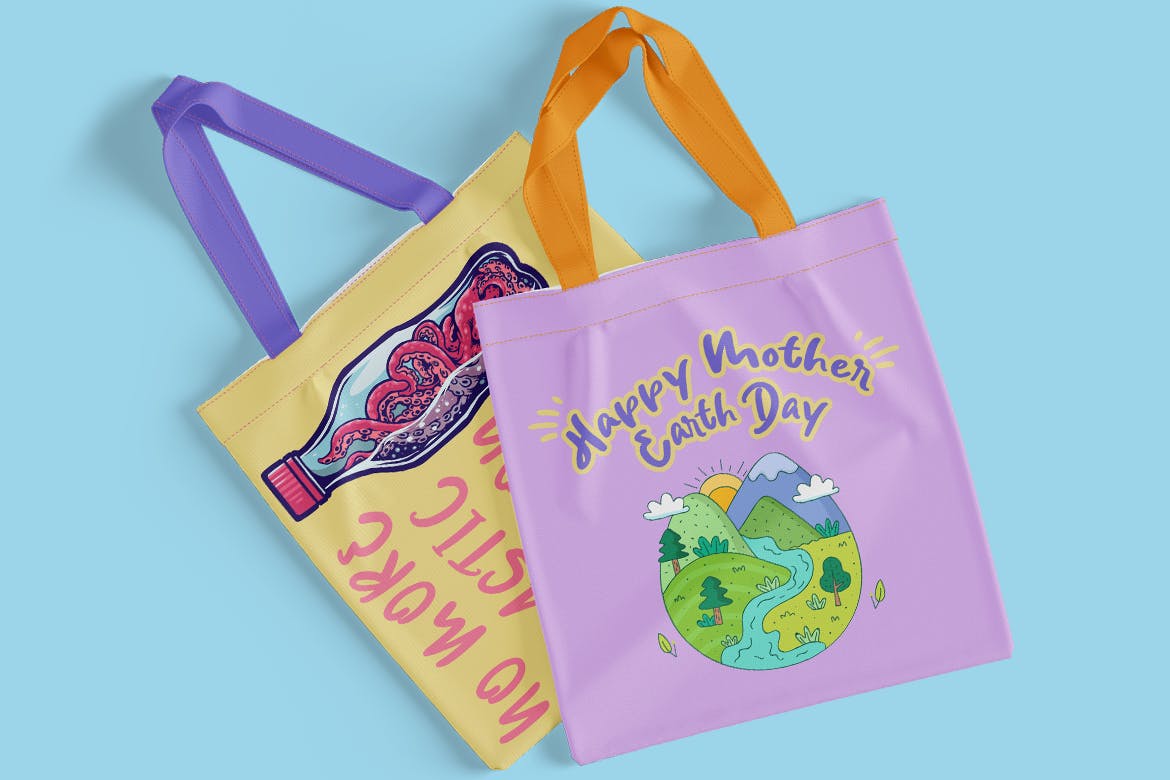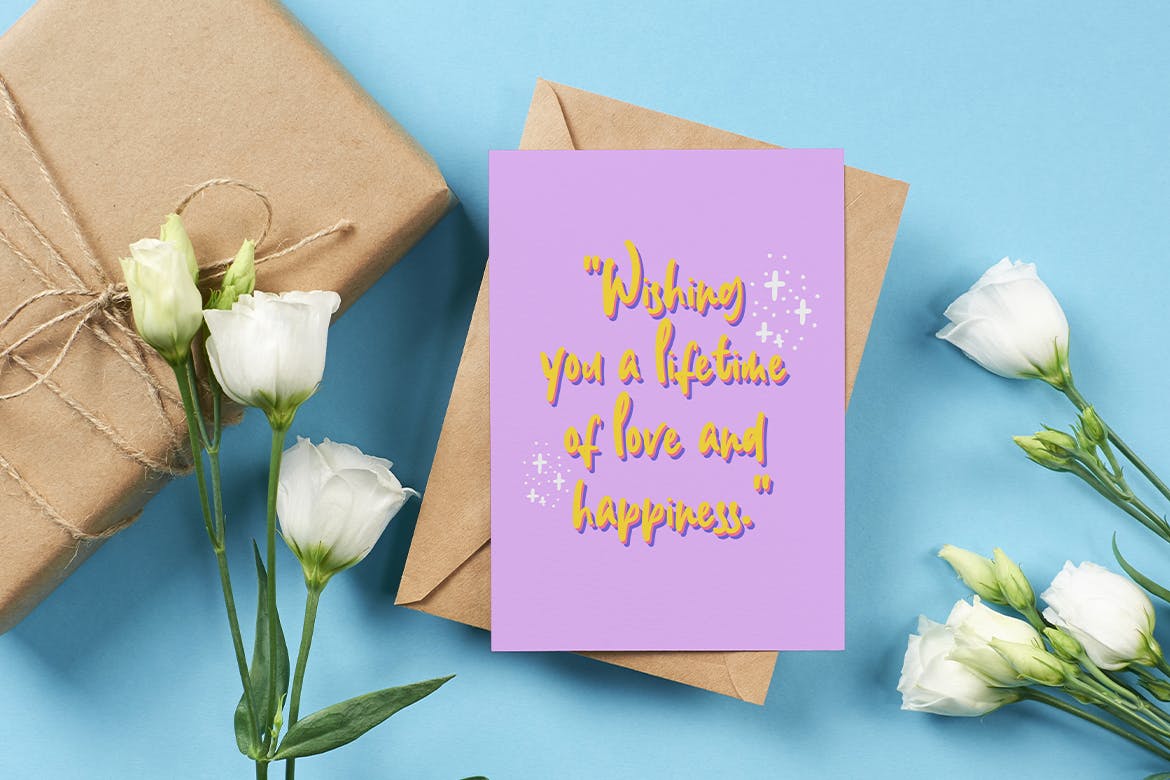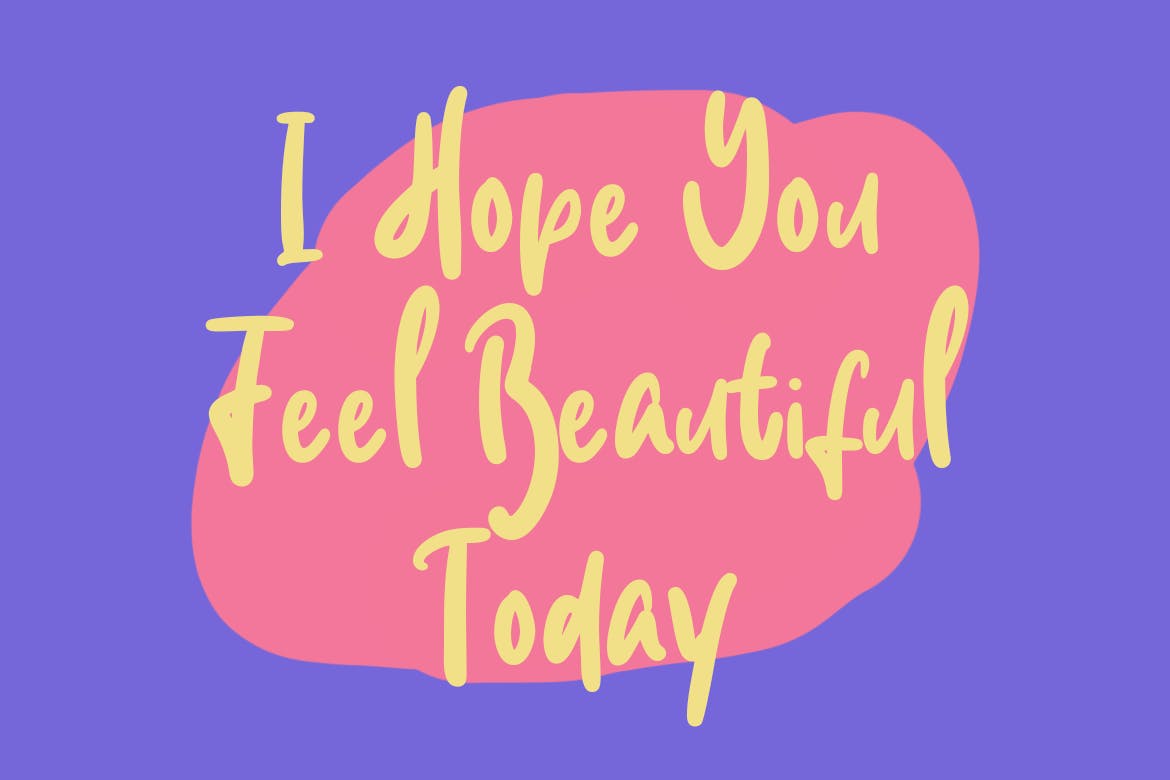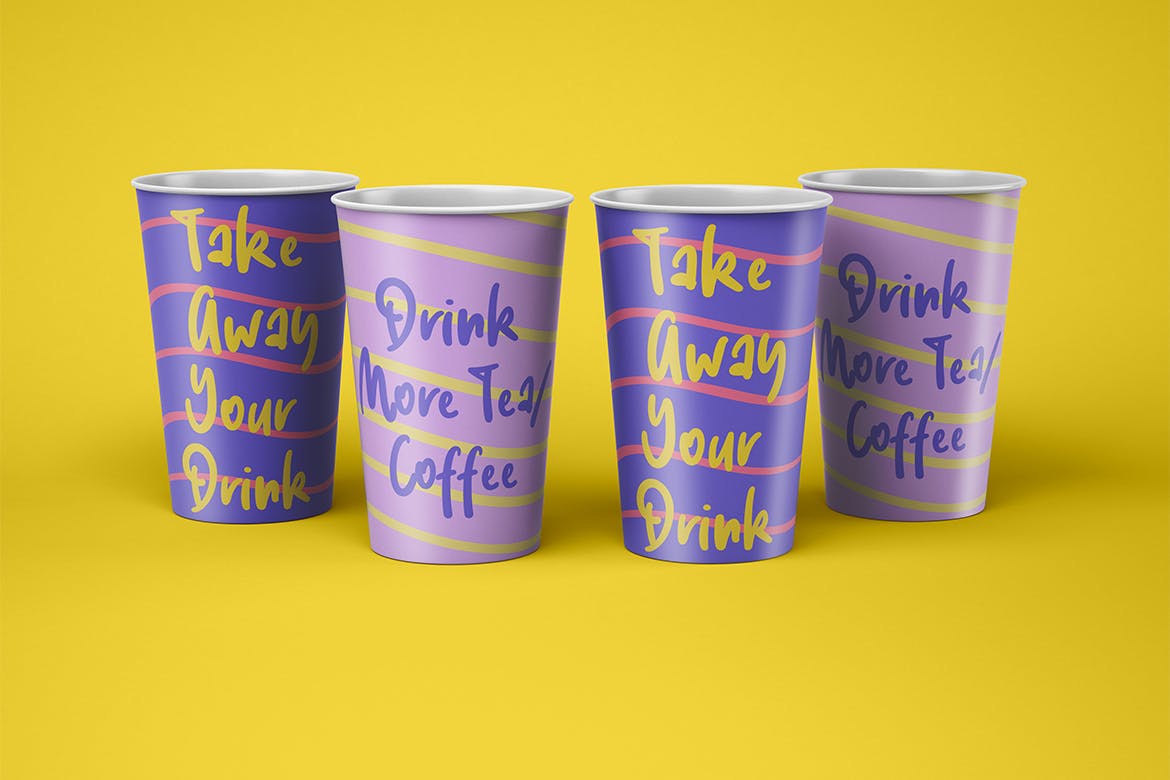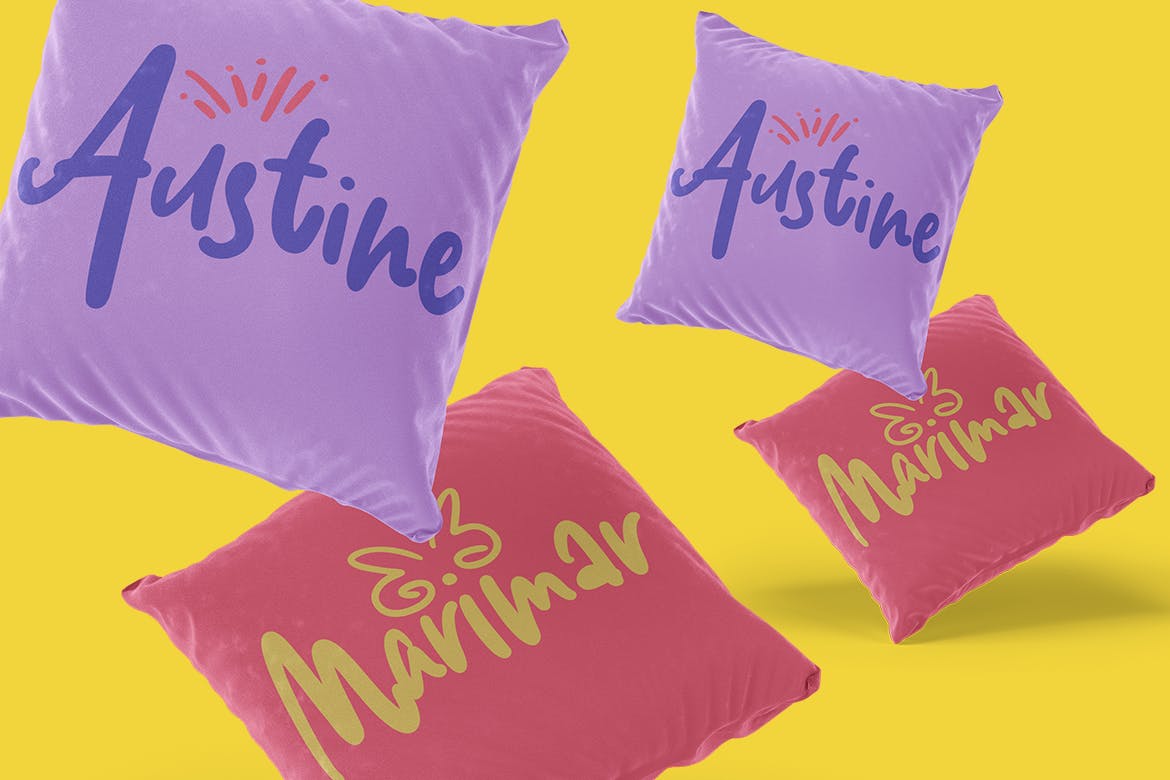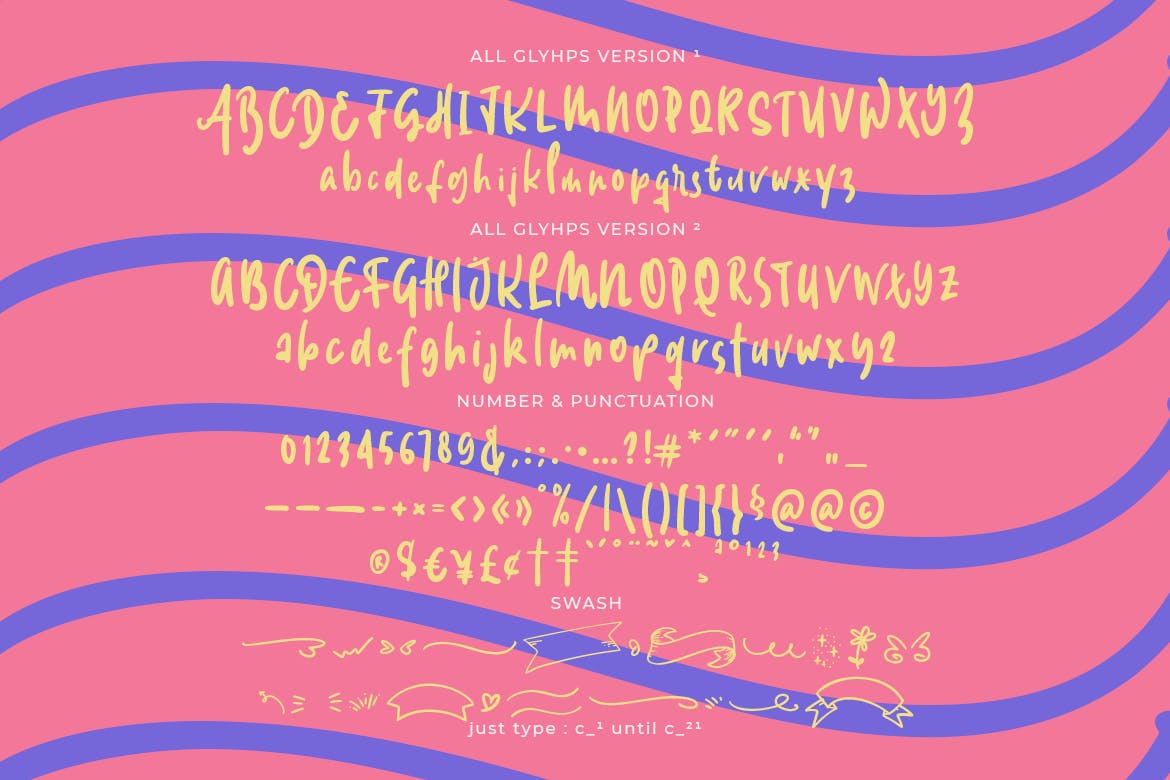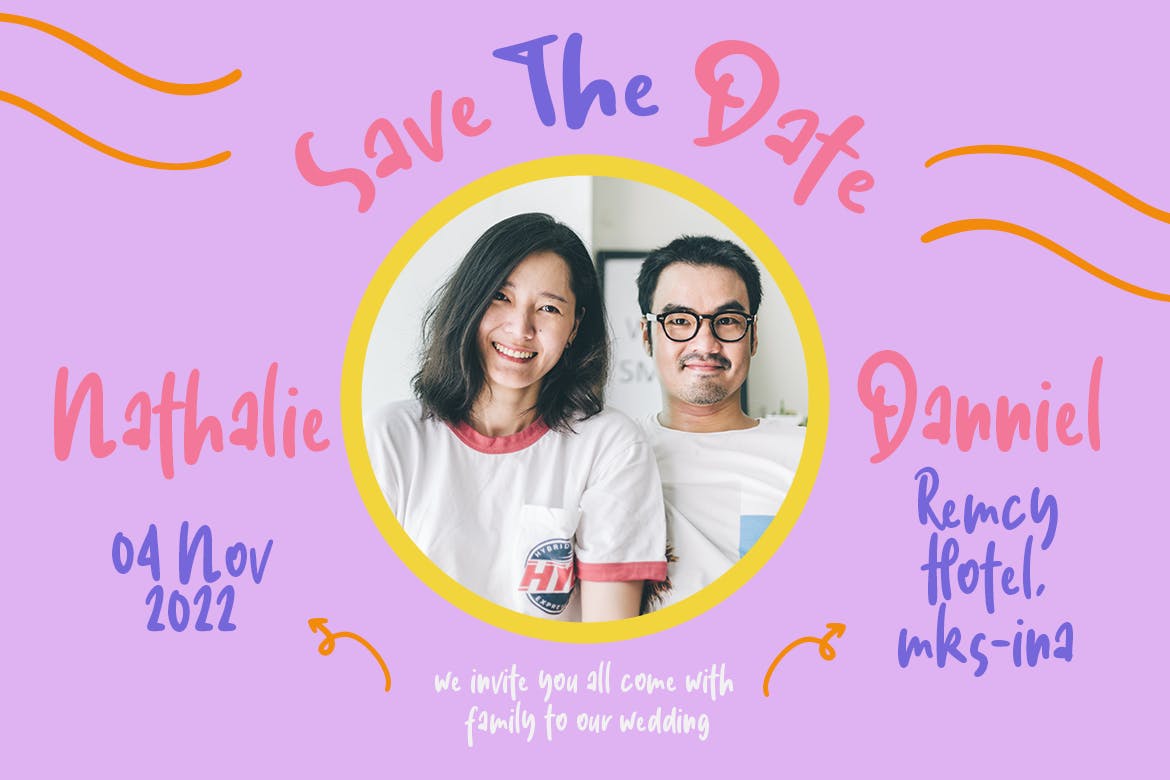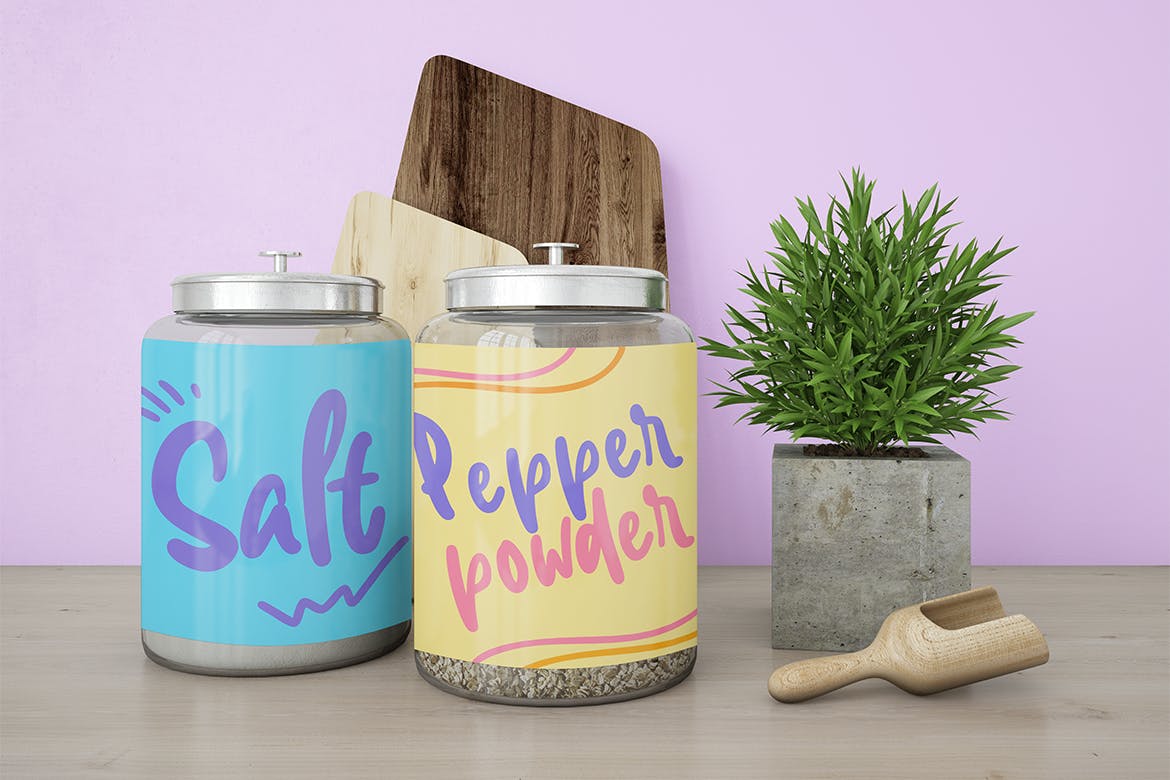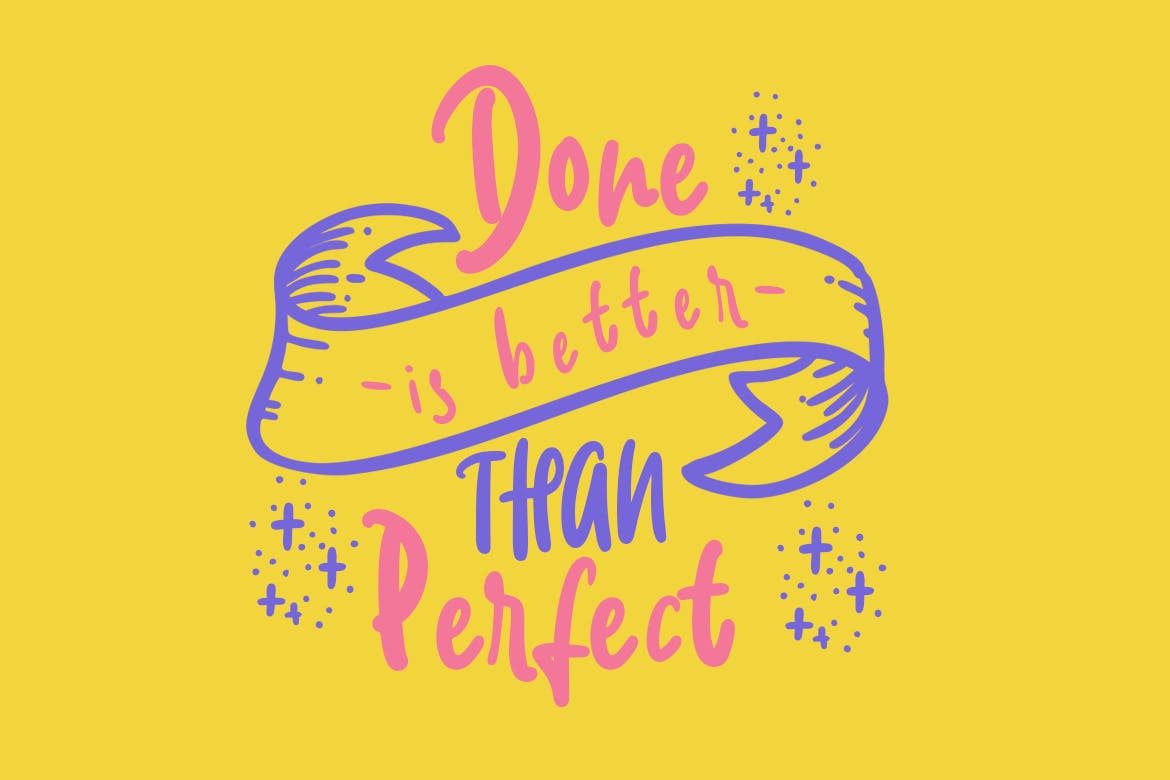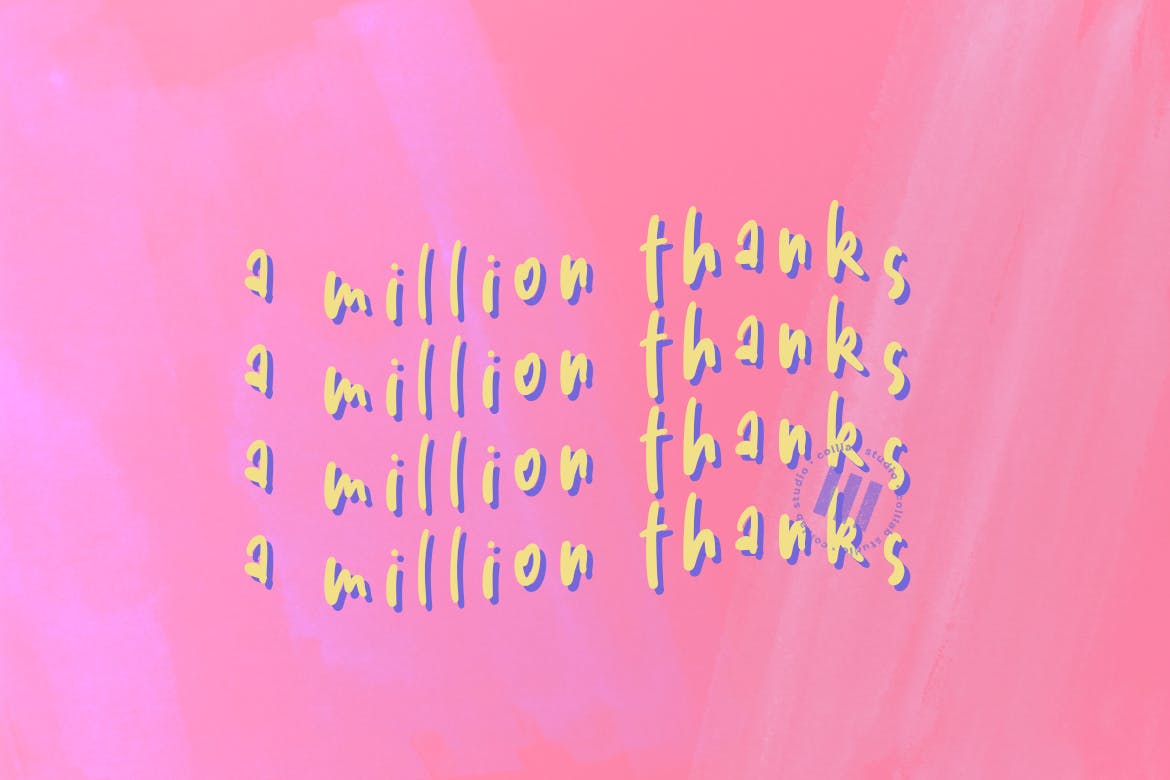
بنابراین ما اینجا هستیم تا بخشی از ناامیدی شما را در جستجوی فونت از بین ببریم، با Hantera: یک فونت جدید و زیبا که ظرافت و لوکسی را به نمایش میگذارد اما همچنان سرگرمکننده است. این فونت بسیار چندمنظوره است و به عنوان یک افزودنی عالی برای پروژه طراحی بعدی شما، چه دعوتنامههای عروسی باشد یا کارتهای تبریک و هر چیزی در بین آنها، عمل میکند. این فونت برای هر پروژهای که نیاز به لمسه شخصی دارد، ایدهآل است.
Hantera شامل حروف بزرگ و کوچک، اعداد، نشانهگذاری و پشتیبانی از زبانهای مختلف است. همچنین شامل ویژگیهای OpenType مانند Alternates متنی و Stylistic Alternates برای افزودن تنوع به متن میباشد.
ویژگیها: